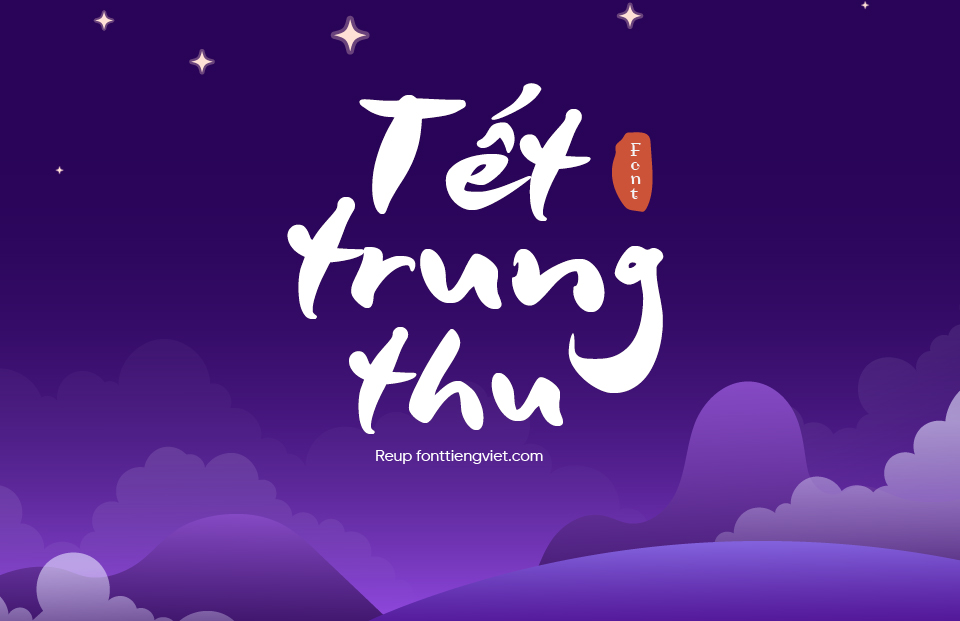
Font Việt hóa LNTH DeBorstel Brush – Font trung thu
Font Việt hóa LNTH DeBorstel Brush – Font trung thu chuyên dụng cho thiết kế sáng tạo
Trong thị trường thiết kế đồ họa hiện nay, việc tìm kiếm một bộ Font Miễn Phí có phong cách độc đáo để phục vụ cho các dịp lễ hội truyền thống luôn là ưu tiên hàng đầu của các nhà thiết kế. Font Việt hóa LNTH DeBorstel Brush – Font trung thu nổi lên như một sự lựa chọn hoàn hảo nhờ sự kết hợp tinh tế giữa nét vẽ tay mộc mạc và sự linh hoạt của phong cách brush hiện đại. Đây không chỉ là một bộ phông chữ thông thường mà còn là linh hồn giúp các ấn phẩm thiết kế trở nên sống động và đậm chất nghệ thuật dân gian hơn bao giờ hết.
Đặc điểm nổi bật của Font Việt hóa LNTH DeBorstel Brush – Font trung thu
Bộ phông chữ này được thiết kế dựa trên cảm hứng từ những nét bút lông mạnh mẽ nhưng không kém phần uyển chuyển. Đặc trưng lớn nhất của LNTH DeBorstel Brush chính là các đường nét thô ráp tự nhiên, tạo cảm giác gần gũi và chân thực cho người xem. Khi được ứng dụng vào chủ đề lễ hội, Font Việt hóa LNTH DeBorstel Brush – Font trung thu giúp tái hiện hình ảnh những chiếc đèn lồng rực rỡ hay những mâm cỗ đêm rằm một cách trọn vẹn nhất.
Khả năng tương thích và Việt hóa chuẩn chỉnh Font Việt hóa LNTH DeBorstel Brush
Một điểm cộng lớn của bộ font này chính là việc đã được Việt hóa hoàn chỉnh, bao gồm đầy đủ hệ thống dấu tiếng Việt mà không xảy ra tình trạng lỗi hiển thị hay mất nét. Điều này cực kỳ quan trọng đối với các bạn học sinh và giáo viên khi cần trình bày các bài thuyết trình về ngày Tết Thiếu nhi hay thiết kế thiệp mời cho các hoạt động ngoại khóa tại trường học. Bạn có thể dễ dàng sử dụng phông chữ này trên nhiều phần mềm thiết kế phổ biến như Photoshop, Canva hay thậm chí là Microsoft Word mà vẫn đảm bảo được tính thẩm mỹ cao nhất.
Vẻ đẹp nghệ thuật từ phong cách Brush
Phong cách brush (bút cọ) của LNTH DeBorstel mang lại sự phóng khoáng, giúp phá vỡ những quy chuẩn cứng nhắc của các font chữ truyền thống. Các ký tự có độ cao thấp không đồng nhất tạo nên nhịp điệu thị giác thú vị, khiến nội dung văn bản trở nên lôi cuốn và dễ dàng thu hút sự chú ý từ cái nhìn đầu tiên. Đối với các dự án cần sự sáng tạo đột phá, đây chính là “vũ khí” bí mật để tạo nên dấu ấn riêng biệt.
Ứng dụng thực tế của Font Việt hóa LNTH DeBorstel Brush – Font trung thu
Phông chữ này cực kỳ đa năng trong nhiều lĩnh vực thiết kế khác nhau. Bạn có thể sử dụng nó để làm tiêu đề cho các áp phích sự kiện, banner quảng cáo bánh trung thu, hay thậm chí là in ấn lên các bao bì sản phẩm quà tặng. Sự kết hợp giữa nét chữ nghệ thuật và màu sắc rực rỡ của mùa lễ hội sẽ tạo nên một tổng thể hài hòa, mang đậm bản sắc văn hóa Việt Nam.
Thiết kế truyền thông xã hội Font Việt hóa LNTH DeBorstel Brush
Trong thời đại kỹ thuật số, các bài đăng trên Facebook hay Instagram về chủ đề rước đèn, phá cỗ cần những phông chữ bắt mắt để tương tác với người dùng. Sử dụng Font Việt hóa LNTH DeBorstel Brush – Font trung thu sẽ giúp nội dung của bạn nổi bật giữa hàng ngàn thông tin khác, tạo nên sự chuyên nghiệp và chỉn chu trong từng hình ảnh quảng bá.
Sử dụng trong giáo dục và trang trí lớp học Font Việt hóa LNTH DeBorstel Brush
Tại các trường học, giáo viên có thể dùng font chữ này để thiết kế các bảng tin, phông nền sân khấu cho ngày hội trăng rằm. Với vẻ ngoài thân thiện, phông chữ giúp các em học sinh cảm thấy hứng thú hơn với những hoạt động truyền thống của dân tộc. Việc lựa chọn một phông chữ phù hợp không chỉ làm đẹp không gian mà còn thể hiện sự tinh tế trong công tác giáo dục thẩm mỹ cho trẻ nhỏ.